Цветные шрифты, похоже, станут сенсацией в мире графического дизайна в 2018 году, но немногие пока представляют, что это такое и как можно использовать такие шрифты. Если не увлекаться техническими аспектами этой тенденции и объяснить все простыми словами, то получается, что этот горячий тренд обещает вернуть веселье в типографику.
Что такое цветные шрифты
Если дизайнер работает над серьезным проектом, то ему лучше использовать векторные символы или группы символов. Или растровые, но в хорошем разрешении. Созданные с нуля дизайнерами-шрифтовиками, подобные сложные изображения смотрятся красиво, но лишены функциональности и гибкости обычного шрифтового файла. По сути, это просто эффектные векторные или растровые иллюстрации, просто в этом смысле арт-объектом выступает буква или символ.
Так было, пока не появилась новая технология. Цветные шрифты, которые иногда называют хроматическими, представляют собой следующий шаг в эволюции типографики. Цветным шрифтам присущи такие характеристики, как цвет, градиенты и текстуры, внедренные в шрифтовой файл. Если файл векторный, то он может масштабироваться, без потери качества, а вот с растровыми версиями все обстоит сложнее: такие шрифты будут выглядеть размытыми, если их размер будет выше установленной максимальной величины.
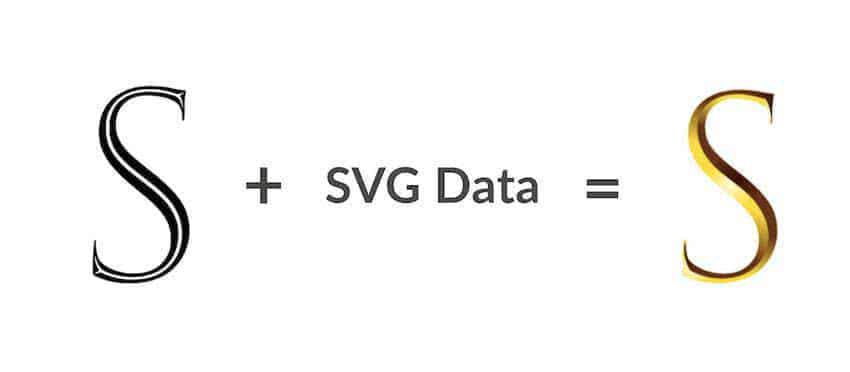
Каждый цветной шрифт состоит из основного ядра, которое содержит стандартный файл OpenType и дополнен данными в формате SVG. Отличить цветной шрифт от обычного несложно, он именуется так: OpenType-SVG. Когда пользователь просматривает типографику в браузере, который поддерживает новую технологию, он может увидеть красочную версию дизайна. Если же нет, то браузер покажет обычный шрифт. Здесь стоит оговориться: цветной шрифт это не просто шрифт, окрашенный в какой-либо цвет. Этого можно добиться с помощью CSS. Нет, цветной шрифт это сложная композиция, где каждый символ тщательно проработан и где используются различные дизайнерские приемы. Так как цветные шрифты тренд относительно новый, большинство браузеров пока не поддерживают эту технологию. Но в ближайшем будущем все изменится.
Как использовать цветные шрифты?
Большинство дизайнеров в начале своей карьеры пережили «шрифтовую лихорадку» — период смелых экспериментов с типографикой. Объемные, светящиеся или «металлические» шрифты – все это поначалу очень интересно, но потом энтузиазм стихает, так как такие шрифты мало где можно использовать. И дизайнер обращается к стандартным шрифтам. С ними работать гораздо проще и безопаснее. К тому же цветной шрифт это не тот тренд, который понравится поклонникам минимализма. Сейчас это больше похоже на баловство – цветной шрифт является полной противоположностью минимализму, его корни уходят в ретро-стиль, где активно использовались смелые оттенки и различные эффекты, такие, как тени, обводки и градиенты.
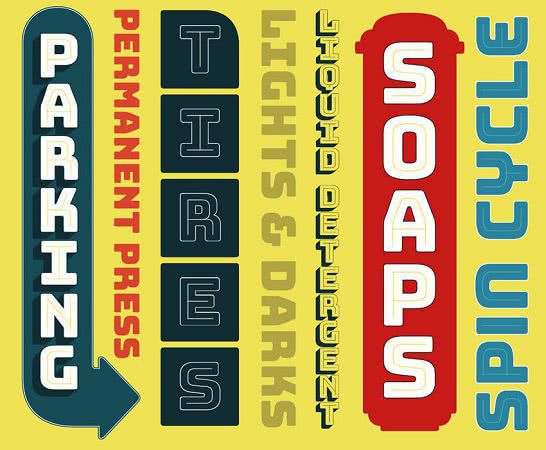
Честно говоря, цветные шрифты сейчас балансируют между хорошим вкусом и полной безвкусицей, но у них определенно есть будущее и они обязательно займут свою нишу. Как только тренд на ретро-дизайн окрепнет, то шрифтовой максимализм проявится в самых разных областях: в печати, моде и даже дизайне интерьеров. Цветные шрифты и позиционируют себя как серьезную тенденцию, у них другая функция – привлекать внимание. Это делает их перспективным инструментом для маркетологов и дизайнеров, которые хотят внести что-то новое в уже сформировавшиеся каноны. Цветные шрифты – это весело. Ранние версии цветных шрифтов создавались для использования в цифровой среде, но все указывает на то, что вскоре появятся подобные гарнитуры и для печати.
Будущее цветных шрифтов
Поскольку цветные шрифты являются новой технологией, многие браузеры, устройства и программные продукты пока не поддерживают новую технологию. Ничего страшного: если в браузере нет поддержки цветного шрифта, он покажет стандартную версию OpenType. Но все изменится очень быстро – шрифты OpenType-SVG уже объявлены отраслевым стандартом, так что ждать обновления браузеров осталось совсем недолго. Сейчас эти забавные шрифты можно просмотреть в поздних версиях Firefox (начиная с версии 26), а также в Microsoft Edge (начиная с версии 38 в Windows 10).
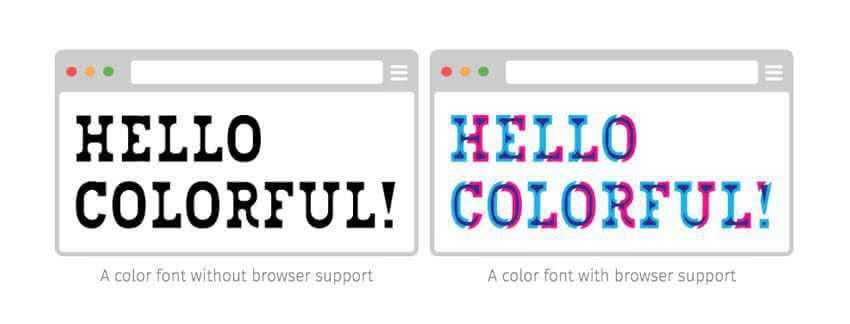
Что касается использования цветных шрифтов в программном обеспечении, то с ними можно работать в таких программах, как Adobe Illustrator (CC 2018), Photoshop (CC 2017) и InDesign (CC 2018). Некоторые дизайнеры уже начали экспериментировать с анимированными версиями цветных шрифтом, так как технология SVG поддерживает анимацию. Такие шрифты можно использовать при работе с редактором Adobe After Effects. Это открывает перед дизайнерами большие возможности и нет сомнений, что анимированная типографика скоро появится повсюду – от социальных сетей до видео.
Сфера применения цветных шрифтов
Если дизайнер пал жертвой соблазна, у него может возникнуть жгучее желание выбросить старые шрифты и полностью перейти на цветные. Но прежде чем начать создавать проекты, напоминающие наркотический бред и галлюцинации, стоит остановиться и немного подумать. Цветные шрифты можно использовать далеко не везде. Как и в случае со стандартными шрифтами, некоторые цветные шрифты выглядят не слишком хорошо. Так что возможность использования далеко не равная обязательной реализации. Пока количество цветных шрифтов невелико, имеет смысл присмотреться к этому тренду. Всего через несколько месяцев таких шрифтов станет гораздо больше, вот тогда и нужно начинать аккуратно внедрять их в свои дизайн-проекты.
Но при этом нужно помнить об ограничениях. Если цветной шрифт является растровым, то не рекомендуется превышать максимальный размер, потому что такой шрифт будет великолепно выглядеть на рекламном флаере, но распадется на пиксели при масштабировании в браузере. Нужно также учитывать, что цветные шрифты весят больше, чем обычный OpenType. Ненамного, но больше, а это может привести к увеличению времени загрузки сайта или приложения.
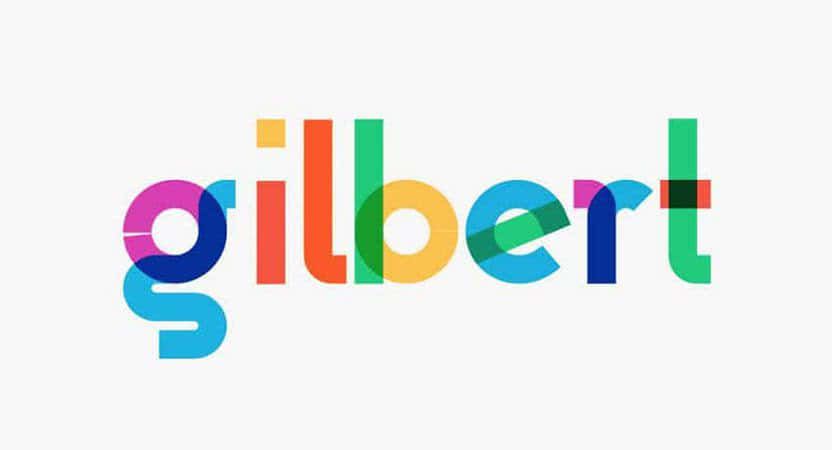
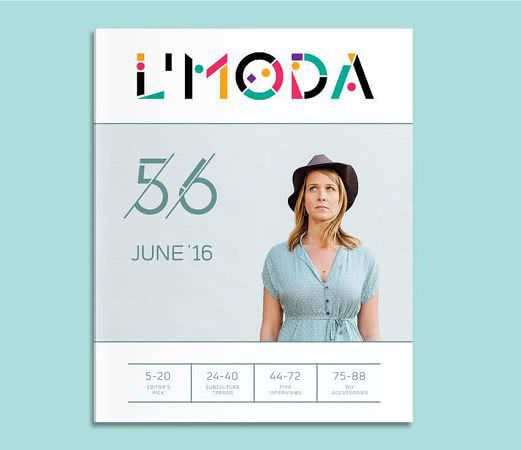
К сожалению, множество пользователей не смогут увидеть результат эксперимента веб-дизайнера с цветными шрифтами. Люди консервативны, они не так часто обновляют браузеры или программные обеспечение. Так что пройдут долгие месяцы или даже годы, прежде чем пользователи смогут увидеть дизайн во всем его великолепии. Это значит, что у цветного шрифта должна быть красивая и сбалансированная основная версия.
Вывод
Цветные шрифты могут стать одним из самых горячих трендов в веб-дизайне. Эта технология позволяет создавать очень эффектные шрифтовые композиции, в том числе и анимированные. Пока еще эта тенденция находится в зачаточном состоянии и цветных шрифтов, доступных для загрузки, совсем немного. Тем не менее, у них есть ясная перспектива и вполне понятные сферы применения. Так что приживется эта тенденция в дизайне или нет, покажет время.